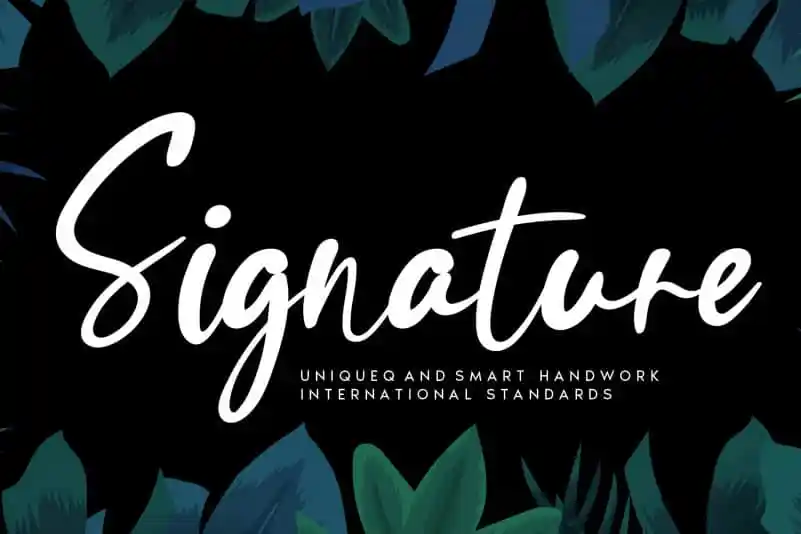
Signature Handwritten Font – Download Grátis
A fonte Signature Handwritten Font é uma elegante escolha para qualquer projeto que busque um toque autêntico e singular. Desenvolvida por andikastudio, ela carrega consigo o charme do traçado a mão, com linhas suaves e detalhes finos, criando designs únicos e memoráveis. Sua característica mais marcante é seu estilo distintivo e único, tornando-a perfeita para criar trabalhos de alta qualidade e design impecável. Seja você um designer profissional ou iniciante, a Signature Handwritten Font oferece uma maneira fascinante de expressar sua criatividade através do texto, garantindo que cada projeto seja memorável e único. Numa era digital, esta fonte representa o equilíbrio perfeito entre tecnologia e arte, permitindo aos designers criar designs verdadeiramente inovadores.